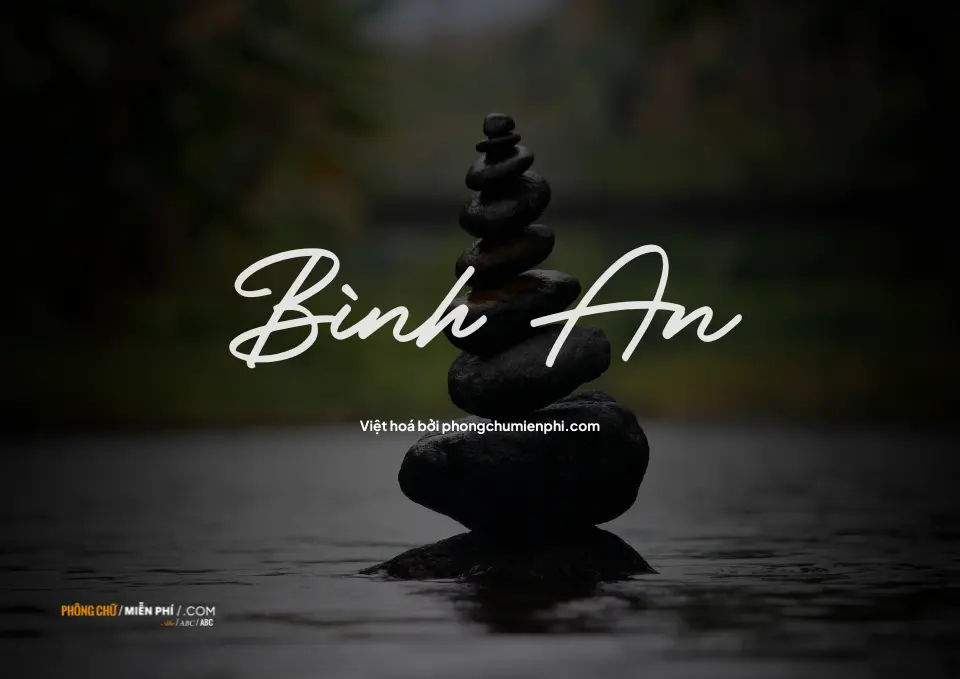
Tên font: Font Việt Hoá Haystack
Font Việt Hoá PCMP Haystack
PCMP Haystack là một kiểu chữ viết tay thanh lịch. Với phong cách hiện đại cùng các chi tiết tinh tế và thanh lịch, Haystack phù hợp cho các ứng dụng xây dựng thương hiệu, cũng như thiệp mời, thiết kế văn phòng phẩm, bài đăng trên mạng xã hội và nhiều hơn thế nữa!